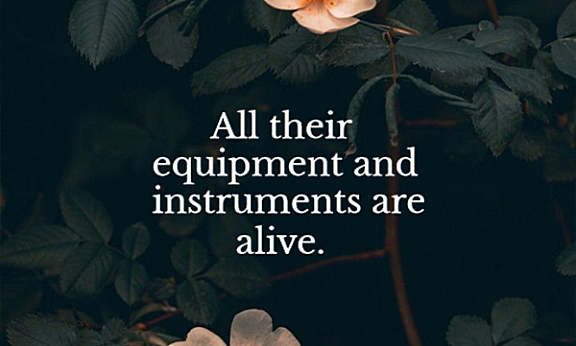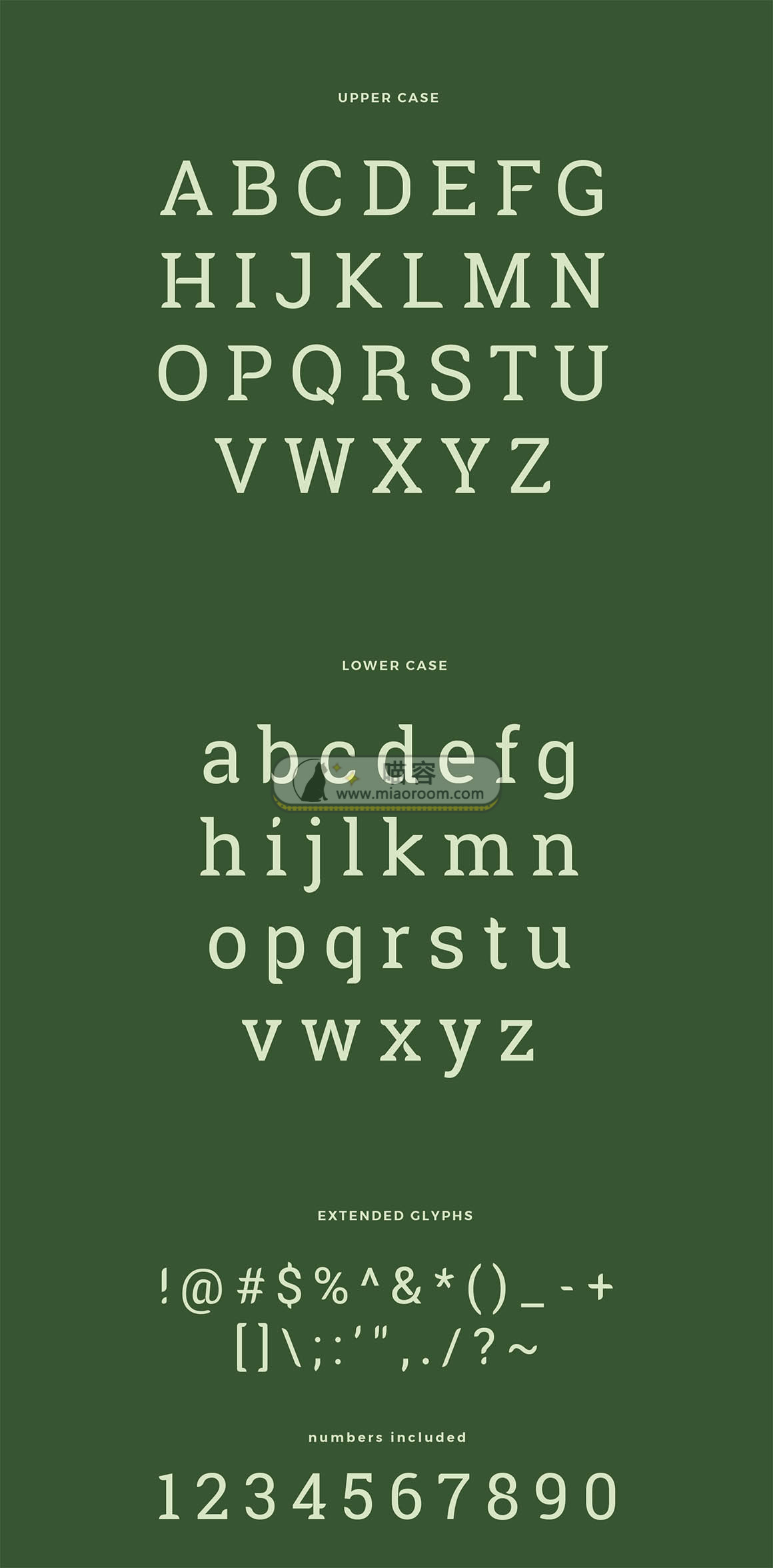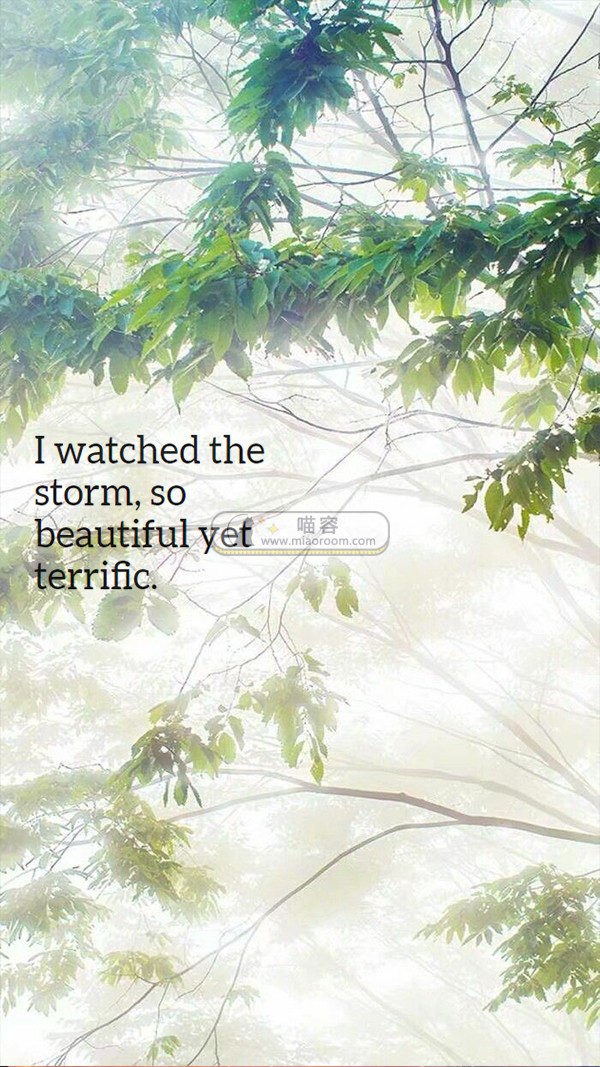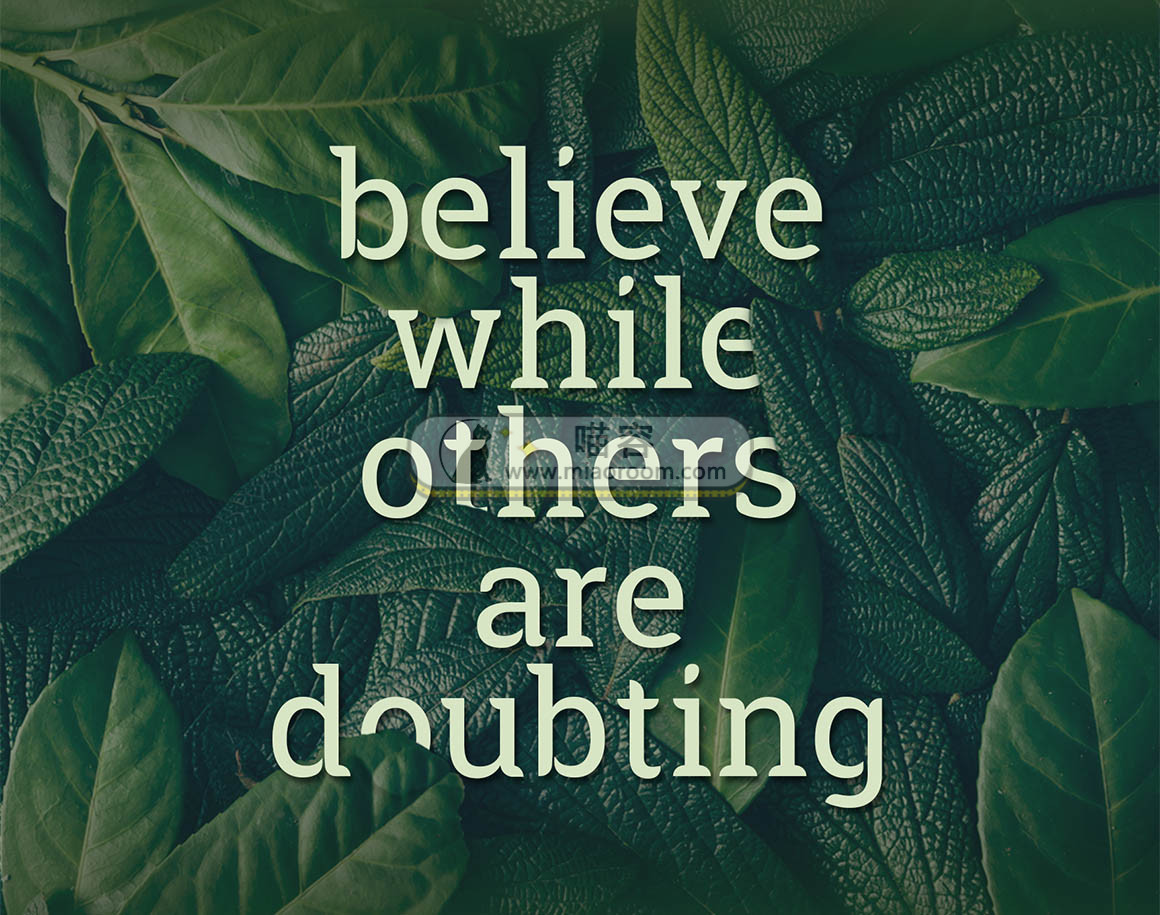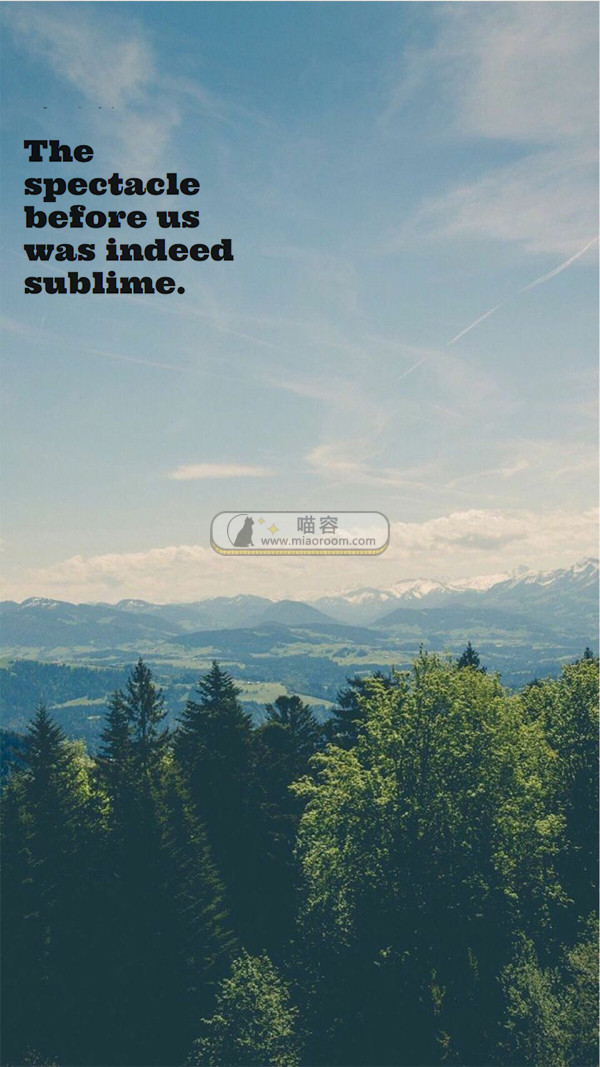
衬线字体应该大家都不陌生,平时阅读和写作都使用的衬线字体,因为衬线字体棱角分明,适合沉浸式阅读。当然衬线字体也可以用于平时的设计中,也会显得有不一样的效果。假如还是设计小白的人,想要在作品中加入一些字,但是字体类型太多了,会让你很伤脑筋。这时候衬线字体就发挥作用了,它适用于大部分风格的作品,在纠结使用哪种字体的时候它应该是最好的选择!下面是我整理的25种衬线字体。
这些字看着没什么特别的,用到不同的图片上还是有不一样的效果的~我随便找了几张图片加上下面的字体,如下图所示。
当然我这些图片都是手机相册里随便找的,有些字体会用的不那么合适,但是在合适的素材上加上这些字看上去确实又是另一种感觉。感兴趣的朋友也可以自己试试哦~